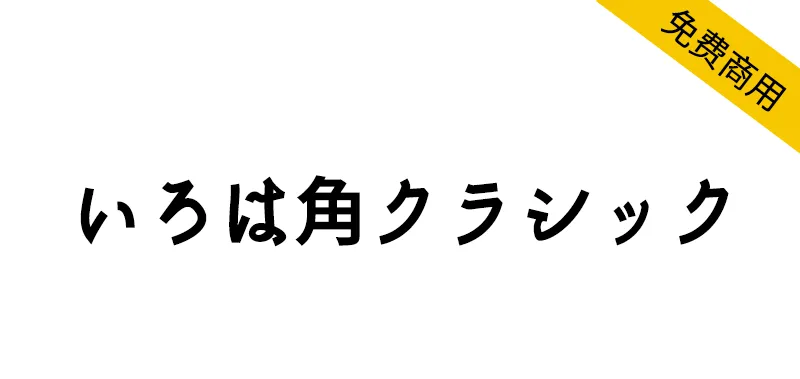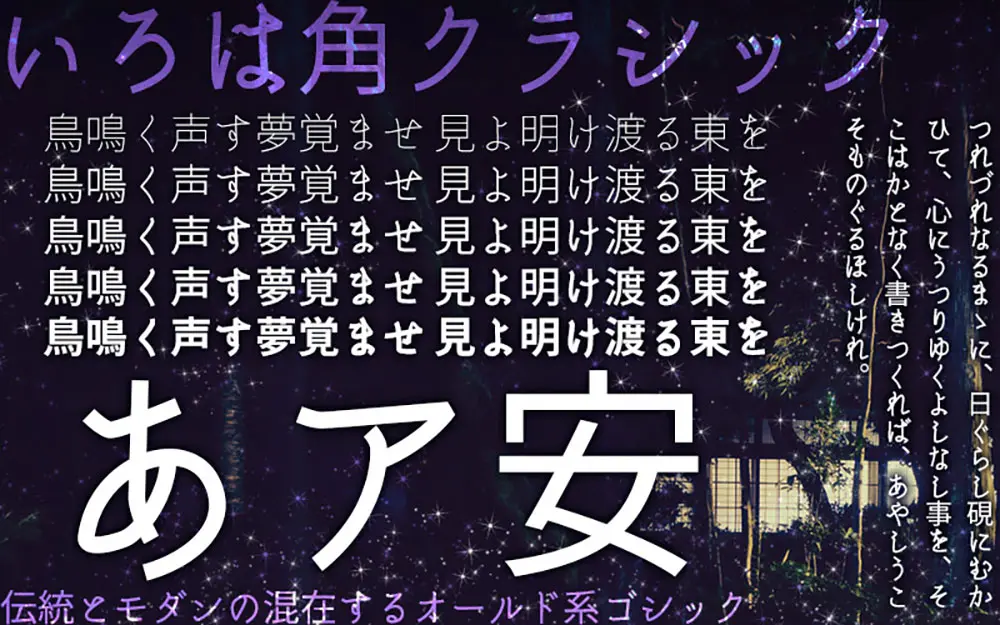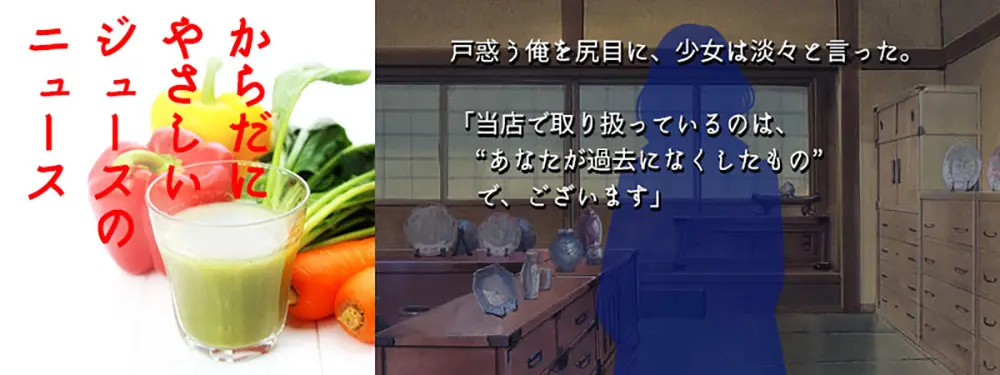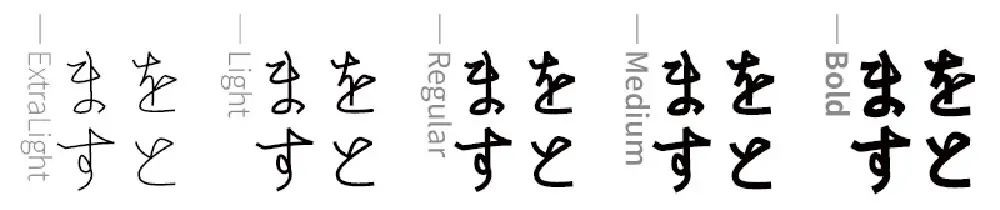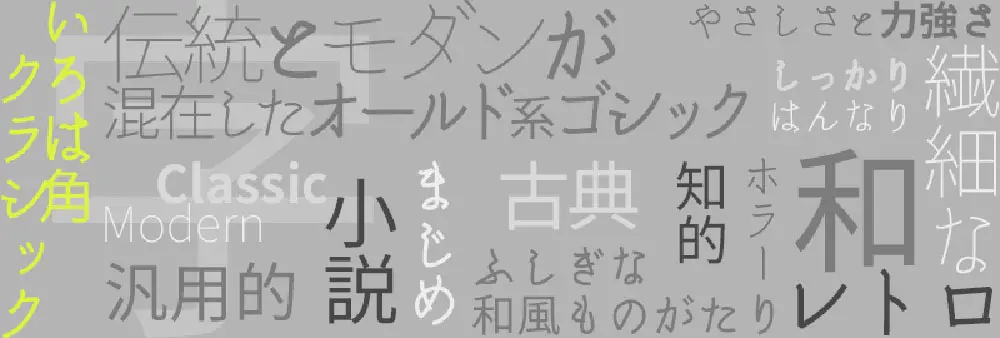
いろは角クラシック預覽
いろは角クラシック介紹
いろは角クラシック是一種修改字體,基於思源黑體的衍生字體思源真黑體(源真ゴシック),並具有原始的平假名、片假名和一些其他符號。這是一種易於使用的字體,結合了老式的字體和現代元素,5個字重。
源ノ角ゴシックの派生フォントである『源真ゴシック(自家製フォント工房/MM様)』の漢字を用い、ひらがな・カタカナ・その他一部記號をオリジナルにした改変フォントです。古風な字形と、現代的なシャープさを合わせ持った、使い勝手の良いフォントです。ウェイト5種。